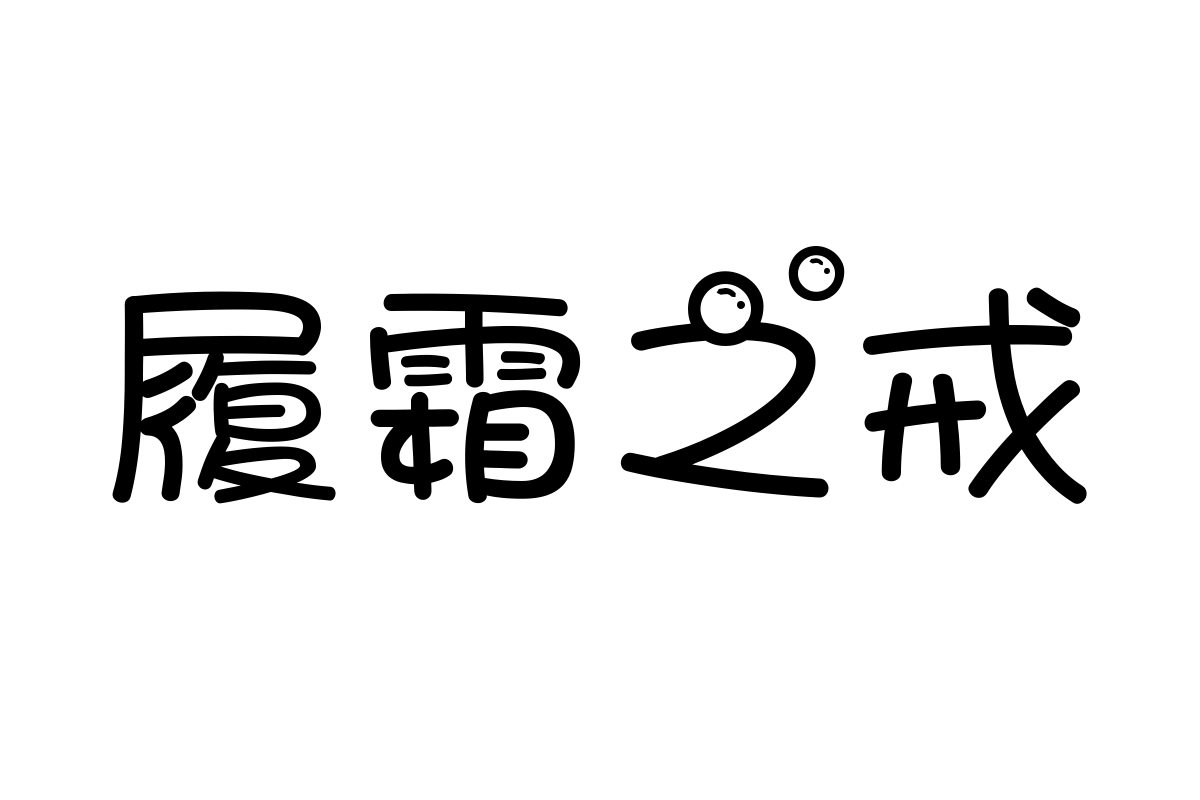
字体管家双鱼座是一款专为中文用户设计的字体,具有独特的艺术风格和个性。这款字体采用了双鱼座的命名方式,象征着双鱼座的神秘、浪漫和梦幻。
字体特点:
1. 字形独特:双鱼座字体的字形独特,线条流畅,给人一种优雅而不失灵动的感觉。
2. 艺术感强:字体设计充满了艺术感,线条弯曲自然,形状各异,仿佛在讲述一个关于双鱼座的故事。
3. 可读性高:虽然字体具有艺术性,但可读性依然很高,无论是阅读还是书写都十分方便。
4. 适用场景广泛:适用于各种需要展现个性化和艺术气息的场景,如设计、广告、印刷等。
总的来说,字体管家双鱼座是一款非常独特且具有艺术感的中文字体,适合用于需要展现个性和艺术气息的场景。